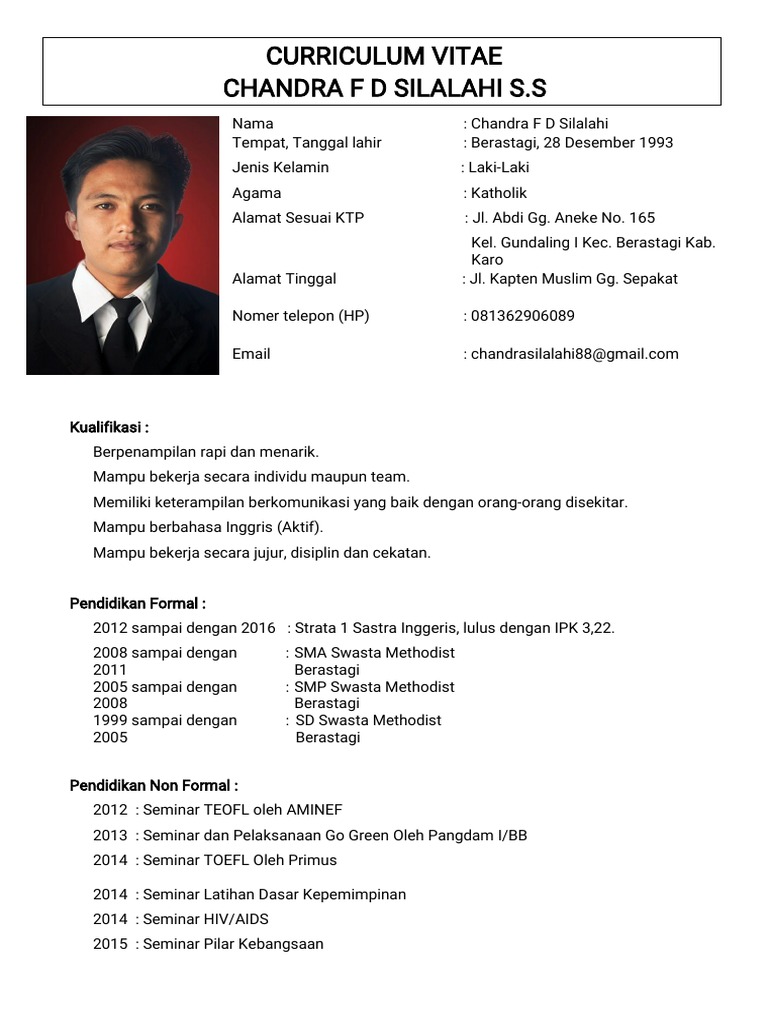
Anda dapat memulainya dengan menggunakan font yang mudah dibaca oleh orang lain untuk itulah artikel ini ditulis lalu anda lanjut menyelesaikan desainnya dari sana lihat bagaimana anda melakukannya disini. Sila pastikan resume anda tidak melebihi 2 muka surat.
Font cv yang baik. Font satu ini resmi menggantikan times new roman sebagai font default pada microsoft word sejak tahun 2007. Namun ternyata tidaklah demikian. Font family nexa termasuk 16 gaya dan bobot yang berbeda beda. Reka bentuk resume bersaiz a4 dan kemasringkas dan tidak mempunyai banyak warna. Memilih font yang kemas dan terang. Jadi memberikan kesan pertama yang baik melalui resume anda adalah hal yang sangat penting membuat resume anda terlihat profesional dan rapi.
Keluarga font ini memiliki keterbacaan yang besar dan bekerja sangat baik sebagai font judul. Cv adalah singkatan dari curriculum vitae atau dalam bahasa indonesia disebut dengan biodatadaftar riwayat hidup. Jangan lupakan unsur warna dan prinsip memilihnya dalam membuat cv ya. Meskipun menjadi default calibri belum digunakan sesering font arial sehingga tidak terlalu pasaran. Sebelum masuk ke contoh cv lamaran kerja sebaiknya kita pahami dulu pengertiannya. Kamu bisa lho menulis isi cv dengan font calibri berukuran 12pt.
Hebatnya setiap cv atau lamaran kerja yang ditulis menggunakan font ini akan terlihat rapih dan sangat cocok dipadukan dengan model dan bentuk cv atau lamaran kerja seperti apapun. Hindari menggunakan font yang berbeda beda pada cv anda karena akan terlihat berantakan. Jadi selalu jaga warna font agar tulisan dan uraian tentangmu tetap nyaman dan jelas dibaca ya. Apapun warna yang kamu pilih tujuan pembuatan cv merupakan pemberian informasi mengenai dirimu. Jenis font untuk cv lamaran kerja agar dilirik perusahaan saat ingin melamar kerja maka seseorang harus membuat curriculum vitae cv atau resume yang kemudian dikirimkan kepada pihak hrd sebuah perusahaancv yang masuk ke perusahaan tersebut mungkin bukan milik anda saja bisa saja ada ratusan cv lain yang menjadi saingan. Font terbaik untuk cv.
Jika dilihat lihat font ini memang nyaman untuk dibaca karena bentuknya yang pas. Contoh menulis deskripsi diri agar cv dilirik rekruter itulah berbagai informasi mengenai warna cv yang baik. Silahkan pilih dan gunakan salah satu diantara beberapa font yang saya sebutkan dibawah ini. Sekilas tentang cv daftar riwayat hidup. Cv merupakan aspek penting pertama yang dapat membuat surat lamaran kerja terlihat menjualmenarik di mata hrd. Bukan rahasia lagi bahwa font yang satu ini menjadi salah satu pilihan font terbaik yang banyak digunakan.
Jenis font ini mengingatkan kita pada times new roman hanya saja lebih terlihat elegan tidak terkesan tidak kaku. Berikut kami berikan beberapa tips dan langkah yang perlu anda lakukan untuk mencipta resume yang baik dan disukai majikan. Banyak orang berpikir bahwa untuk membuat cv yang menarik harus punya kemampuan desain yang baik layaknya seorang desainer. Menurut samantha howie seorang senior manager hrd dari maximum managemen corp yang bermarkas di new york seperti dilansir dari laman huffington post bahwa seseorang bisa membuat cv menarik hanya dengan modal pemilihan font yang tepat. Di sini anda mendapatkan dua bagian dari keluarga secara gratis. Cara buat resume contoh resume lengkap terbaik.
Tomi haaparanta yang terkenal sebagai desainer font yang produktif telah menciptakan jenis huruf baru.